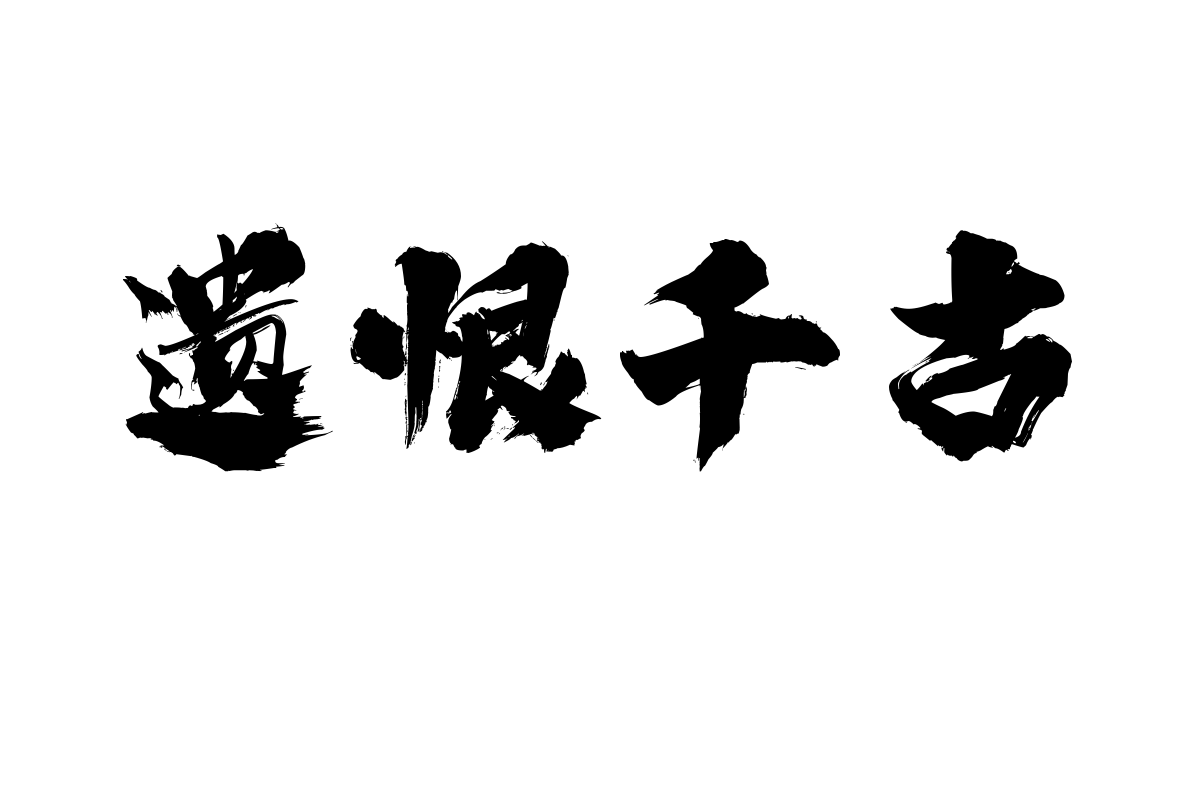
潮字社混元简繁体字体是一款由潮字社设计并发布的字体。这款字体具有独特的设计风格和丰富的字形变化,适用于各种需要展示个性和创意的场合。
潮字社混元简繁体字体的特点如下:
1. 字形独特:该字体采用了独特的字形设计,使得文字在视觉上呈现出独特的美感。无论是笔画、结构还是整体布局,都充满了艺术感和创新精神。
2. 风格多样:潮字社混元简繁体字体涵盖了多种风格,包括现代简约、传统经典、艺术创意等。用户可以根据自己的需求选择合适的风格进行使用。
总之,潮字社混元简繁体字体是一款具有独特风格和丰富表现力的字体,适合用于各种需要展示个性和创意的场合。